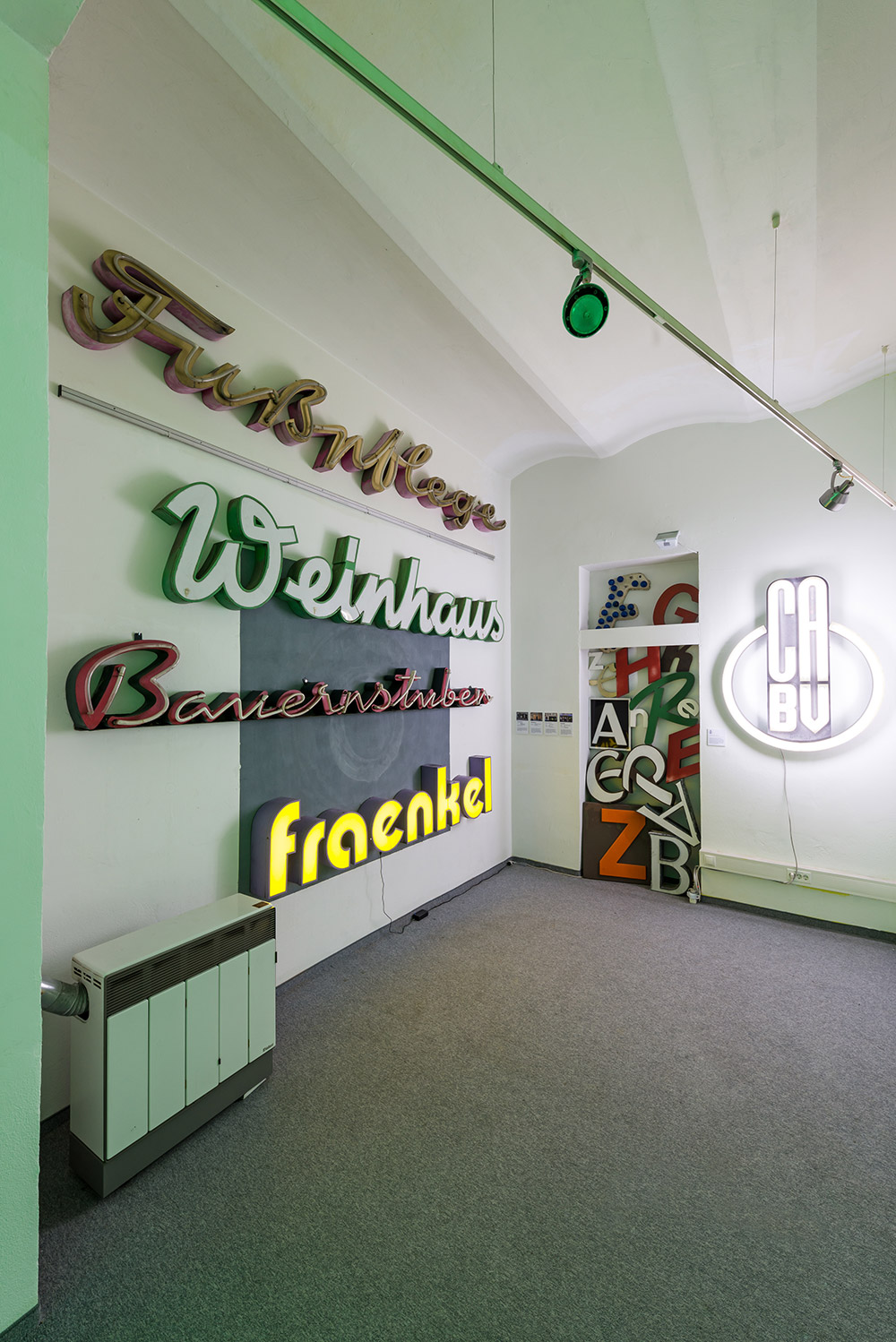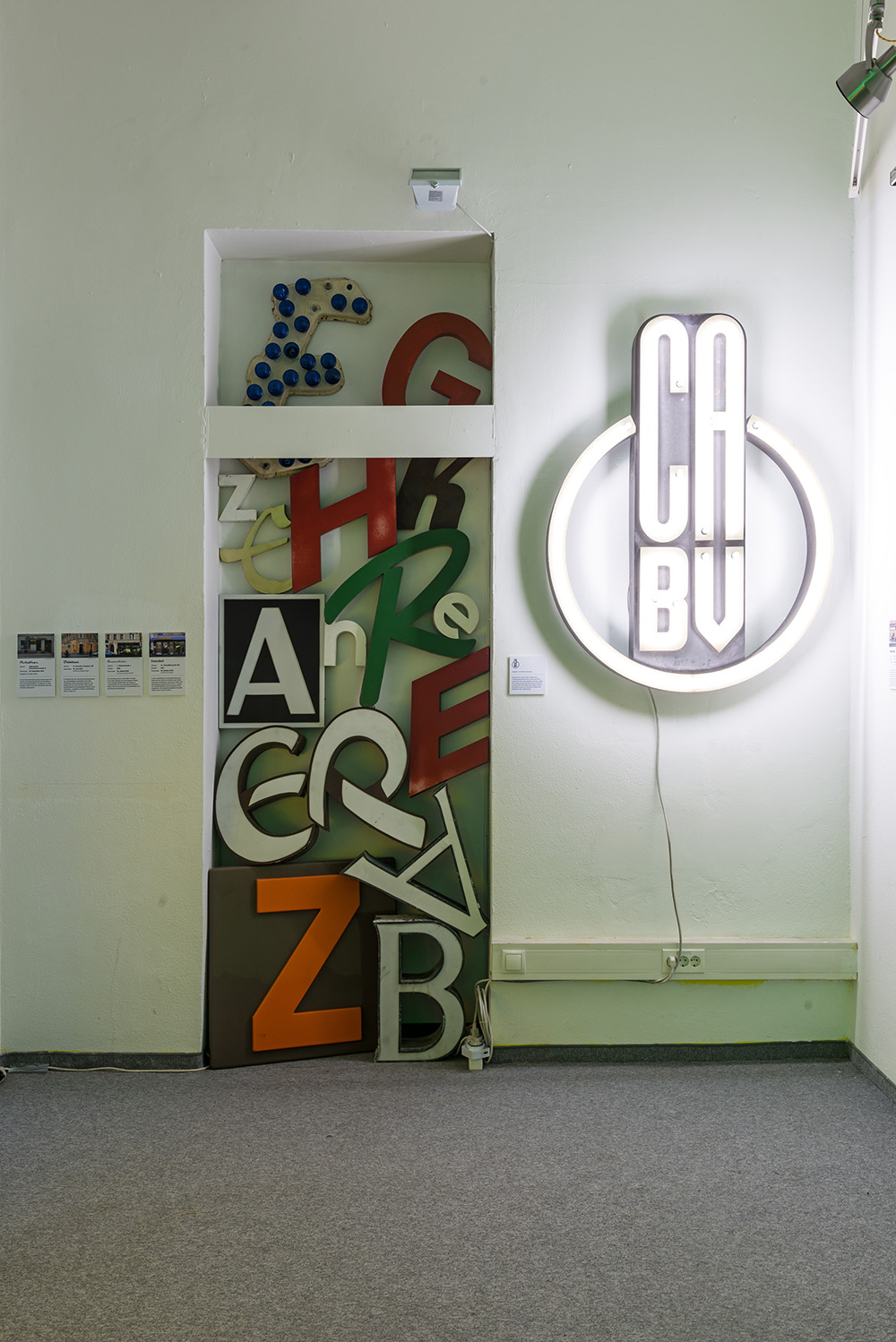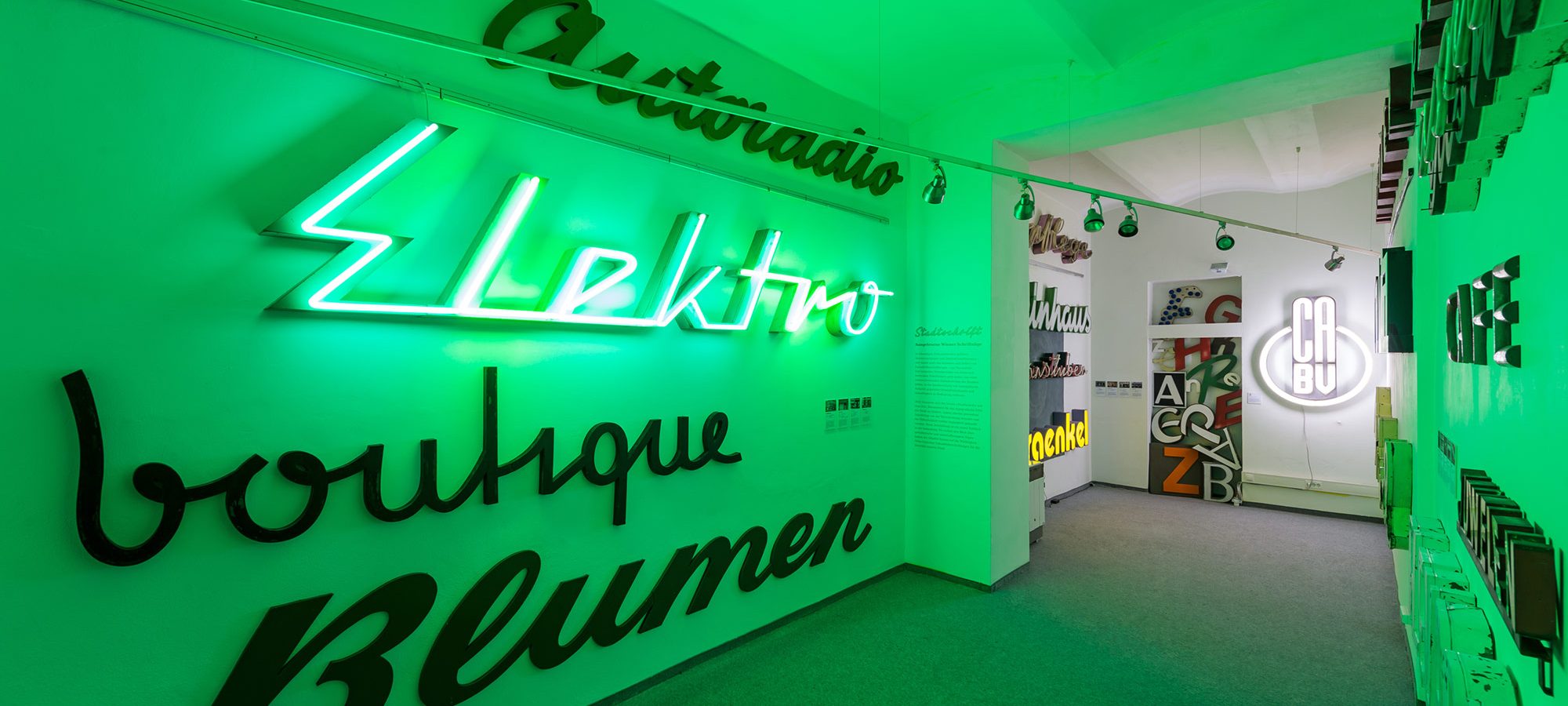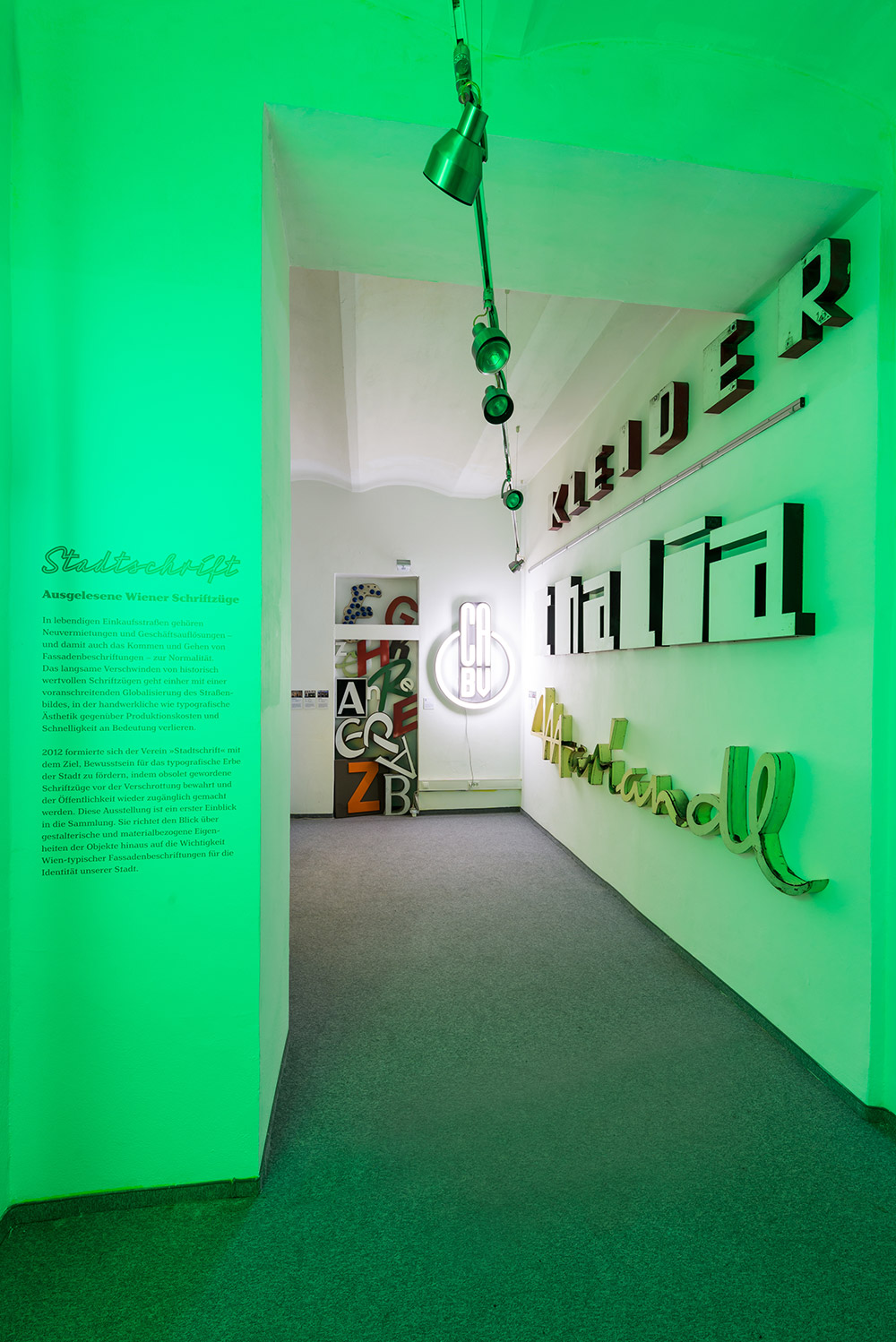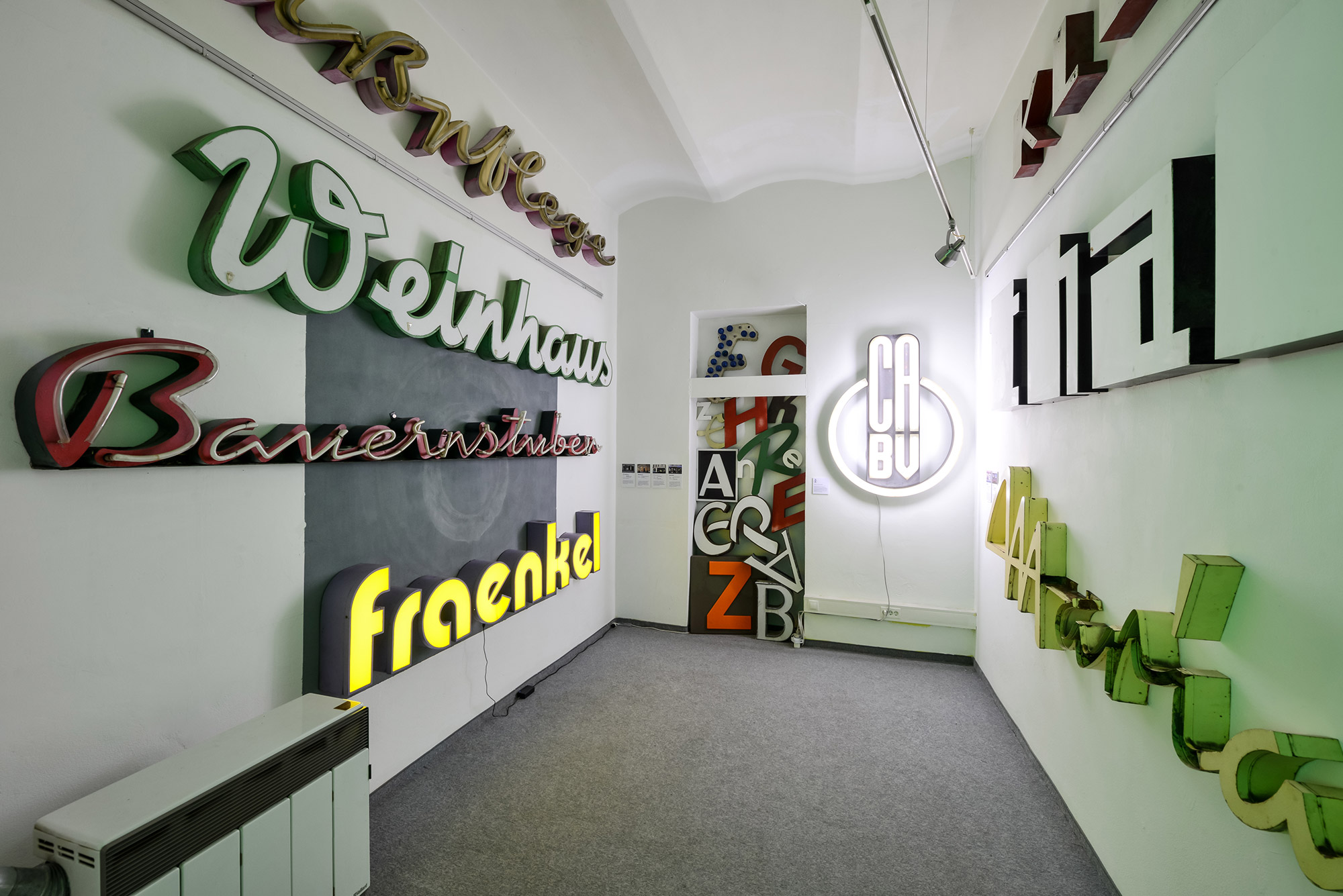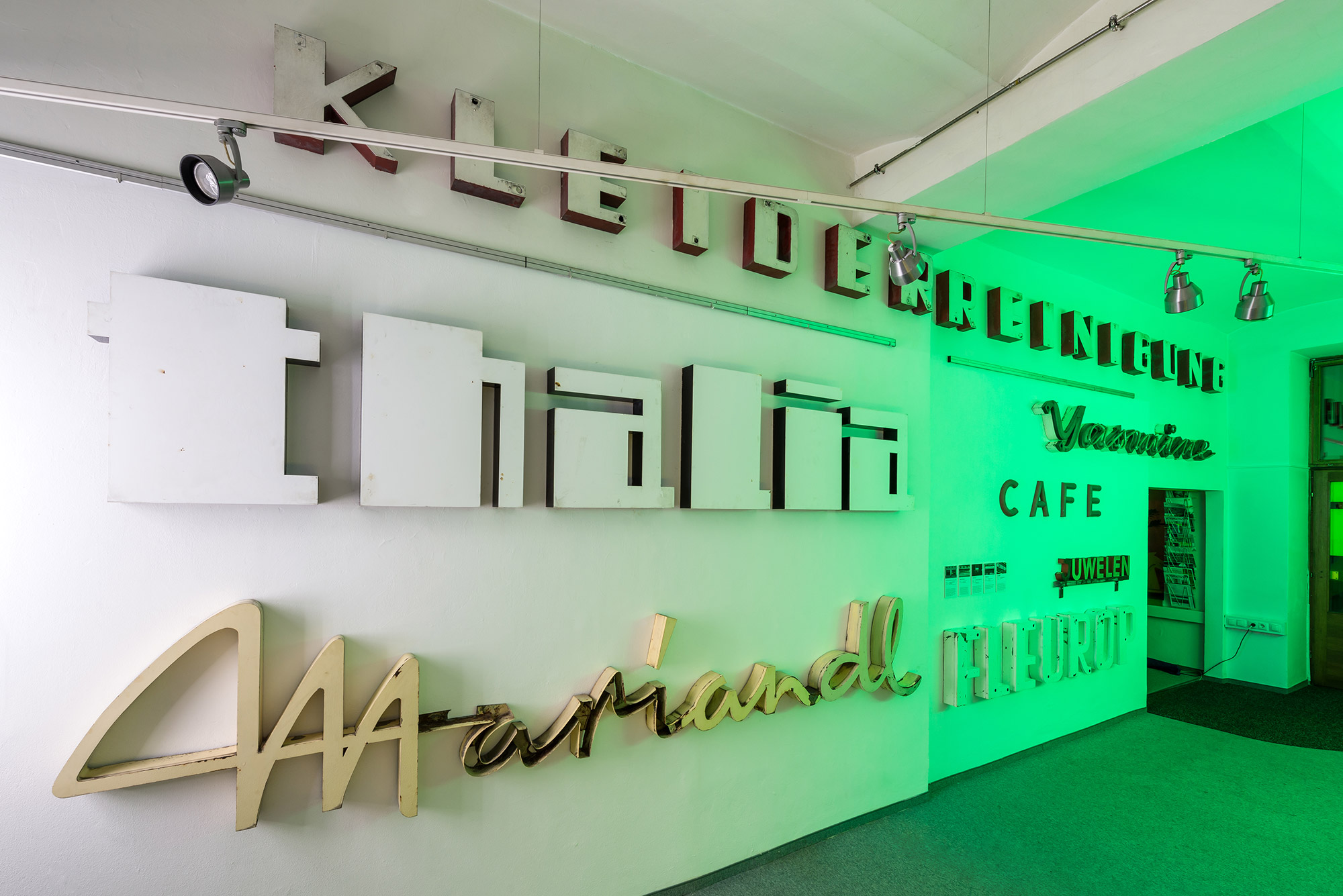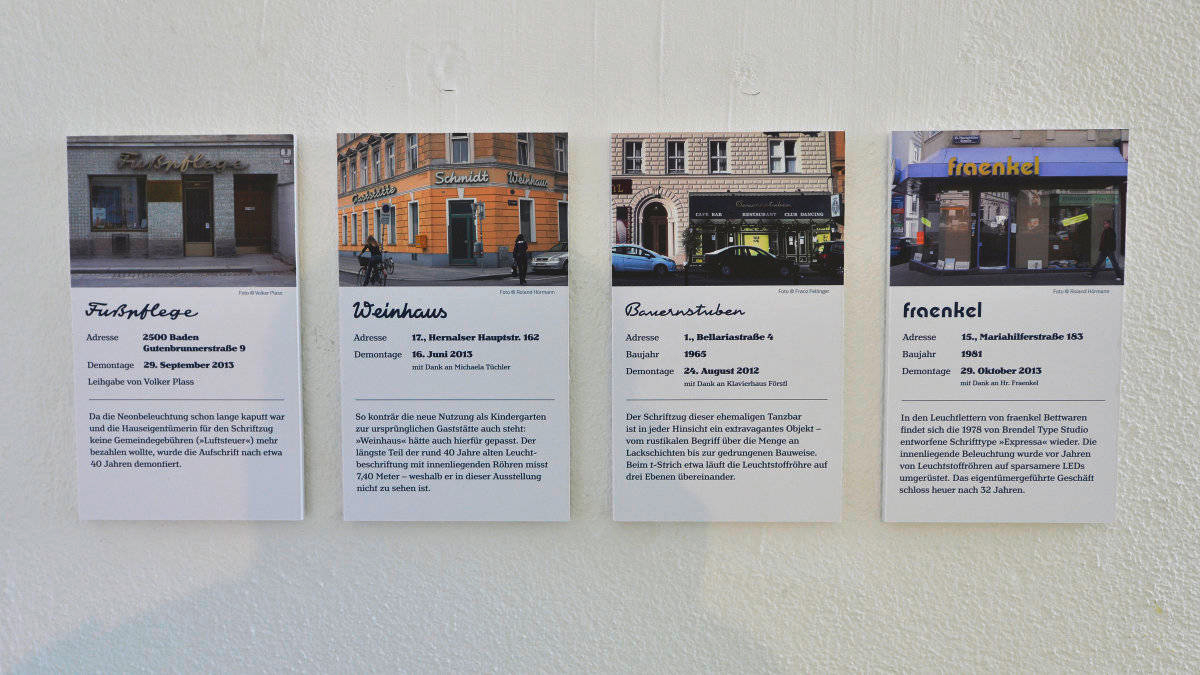
Ausgelesene Wiener Schriftzüge
Ausstellung im Treffpunkt Lerchenfeld, 1070 Wien
November 2013 – März 2014
Mit der Ausstellung im Treffpunkt Lerchenfeld 2013 gab der Verein Stadtschrift einen ersten Einblick in seine Sammlung. Fokus der Ausstellung war es, den Blick über gestalterische und materialbezogene Eigenheiten der Objekte hinaus auf die Wichtigkeit Wien-typischer Fassadenbeschriftungen für die Identität unserer Stadt zu richten.
In lebendigen Einkaufsstraßen gehören Neuvermietungen und Geschäftsauflösungen – und damit auch das Kommen und Gehen von Fassadenbeschriftungen – zur Normalität. Das langsame Verschwinden von historisch wertvollen Schriftzügen geht einher mit einer voranschreitenden Globalisierung des Straßenbildes, in der handwerkliche wie typografische Ästhetik gegenüber Produktionskosten und Schnelligkeit an Bedeutung verlieren.